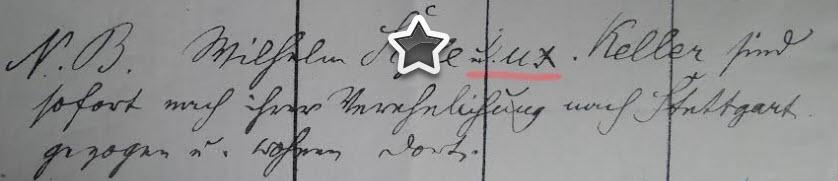
hier ein Fotoausschnitt aus einem Kirchenbuch (ca. 1910).
Wer kann d. rot unterstrichene Wort/Abkürzung lesen?
durch den Stern und die vertikalen Striche kann man den Text an der Stelle nicht lesen, den Kontext so nicht erfassen und damit wird die Aufgabe unnötig schwer bis unmöglich. Gibt es das Bild auch in unversaut? Und ggf. in einer höheren Auflösung? Und was hast Du bisher entziffern können? Mit dem Original kann man das sicher besser lesen, den einige Worte sind für mich hier nicht zu entziffern. Keller ist in lateinischen Buchstaben geschrieben und daher ein Familienname und kein Keller. Schon daher braucht man den vorherigen Satzteil, um zu erkennen ob es sich um einen Namensbestandteil handelt. Und Du hättest den Namen nach N.B angeben können, den der ist sauklauig geschrieben, kann aber dem Eingeweihten durchaus trotzdem schon bekannt sein.
Ich kann da nicht viel erkennen: N. B. ?????? ??????????? Keller sind sofort nach ihrer ?????????? nach Stuttgart gezogen u. wohnen dort.
Stelle die Anfrage also noch mal richtig?
* Quelle (ist korrekt)
* Aussagekräfiges und unversautes Bild in guter Auflösung!1elf
* Text in wie weit Du ihn bisher entziehern konntest
* evtl.e Anmerkungen zum Text die sich aus dem Kontext ergeben (Hinweise auf Namen, Schreibfehler ... )
Was Du da machst ist ungefähr so: Ich habe da eine Information, die ich nicht lesen kann. Deshalb mach ich da noch mal eine Störinformation (Stern) drauf um auch ganz sicher das Lesen zu erschweren. Und dann enthalte ich dem Leser auch noch meine bisher gewonnenen Informationen vor. Ich mache alles also so schwer wie möglich.
Dateinamen können beliebig vergeben werden. Dieser Hinweis auf den Bekannten Vornamen kann/soll/muss in den Text. Mit Mücks Hinweis auf die Verehelichung wird der Kontext nun eindeutig. Vorher habe ich den nur erraten. Jetzt fehlt nur noch eine unverdaddelte Version des Bildes mit freier Sicht auf dem kompletten Namen.
tut mir leid, wenn ich durch Überstempeln eines Wortes "die Aufgabe unnötig schwer bis unmöglich" gemacht habe. Ich sehe das nicht so dramatisch.
Es handelt sich dabei lediglich um einen Nachnamen, sagen wir Schmidtle, Schulze oder Saile...,
was zum Verständnis des Kontextes nicht unbedingt nötig ist.
Was ich schon raus bekam, war:
-----------------------------------------------------
N.03. Wilhelm S. xxx Keller sind
sofort nach ihrer Verehelichung nach Stuttgart
gezogen u. wohnen dort.
-----------------------------------------------------
Man sieht, es fehlt nur der unterstrichene Teil in meiner Entzifferung.
Es könnte ux heißen, macht aber für mich keinen Sinn, deshalb die Anfrage hier im Forum.
Das Bild ist bei mir auf dem BS gestochen scharf (mit 96 dpi) und selbst wenn ich es mit 300 dpi mache, ist es nicht viel schärfer.
Das weiß aber der Betrachter ohne Hintergrundwissen nicht. Keine Information kann auch eine Information sein. Und hier würde es das Erkennen der Wortgrenzen ermöglichen.. Dazu später noch was ...
Was ich schon raus bekam, war:
-----------------------------------------------------
N.03. Wilhelm S. xxx Keller sind
sofort nach ihrer Verehelichung nach Stuttgart
gezogen u. wohnen dort.
-----------------------------------------------------
Man sieht, es fehlt nur der unterstrichene Teil in meiner Entzifferung.
Es könnte ux heißen, macht aber für mich keinen Sinn, deshalb die Anfrage hier im Forum.
Mit der Information ist man aber schon weiter. Vor- und Nachname des Familenoberhäuptlings und seines ange- und vertrauten Weibchens sollte man da erwarten. Keller ist also sehr wahrscheinlich der Geburtsname des Weibchens. Dann erwartet man so was wie den Vornamen des Weibchens und/oder ein Hinweis auf Keller als Geburtsname. Das x könnte auch ein einfaches Kreuz im Sinne von durchstreichen sein? vor dem vmtl. ux. steht noch ein Krackel. Der gehört also noch zum Nachnamen des Männchen? Diese Information hat definitiv gefehlt.
jetzt habe ich in einem anderen Dokument nach dieser Frau, bzw. nach diesem "Fräulein" Keller geschaut, und herausgefunden, dass sie mit Vornamen Luise hieß.
Dann könnte das rot unterstrichene Textteil evtl. Lui. geheißen haben und der letzte Buchstabe ist dann (nachträglich) vom Pfarrer durchgestrichen worden (warum auch immer). Jetzt steht da Lux., was natürlich keinen Sinn gab, aber so ist es erklärbar.
Gruß und Dank an die Helfer.
Könnte es auch "N.B."  (Nebenbemerkung) statt "N.03." heißen? Könnte sich aus dem Kontext ergeben, wenn drüber bspw. die Ehe selbst eingetragen ist ...
Mir fehlt irgendwie was trennendes/verbindendes zwischen den Namen "Wilhelm X und Lu. Keller",  "Wilhelm X, Lu. Keller", "Wilhelm X & Lu. Keller", ... Da könnte sich auch etwas aus anderen Einträgen ergeben ... Oder es versteckt sich unterm Stern ... Bei "Lui." wäre noch der i-Punkt da, also eher eine Falschschreibung korrigiert ...
Daß da immer wieder mal  Latein- Buchstaben oder Worte auftauchen , darf nicht wundern!
Latein war damals, und ist es lange auch in der reformierten Kirche, zumindest "in den Büchern"
geblieben, die Amtssprache der (katholischen ) Kirche  .
Kann das unter dem Stern vielleicht auch eine  etwas lateinisierte "Sophie" sein?